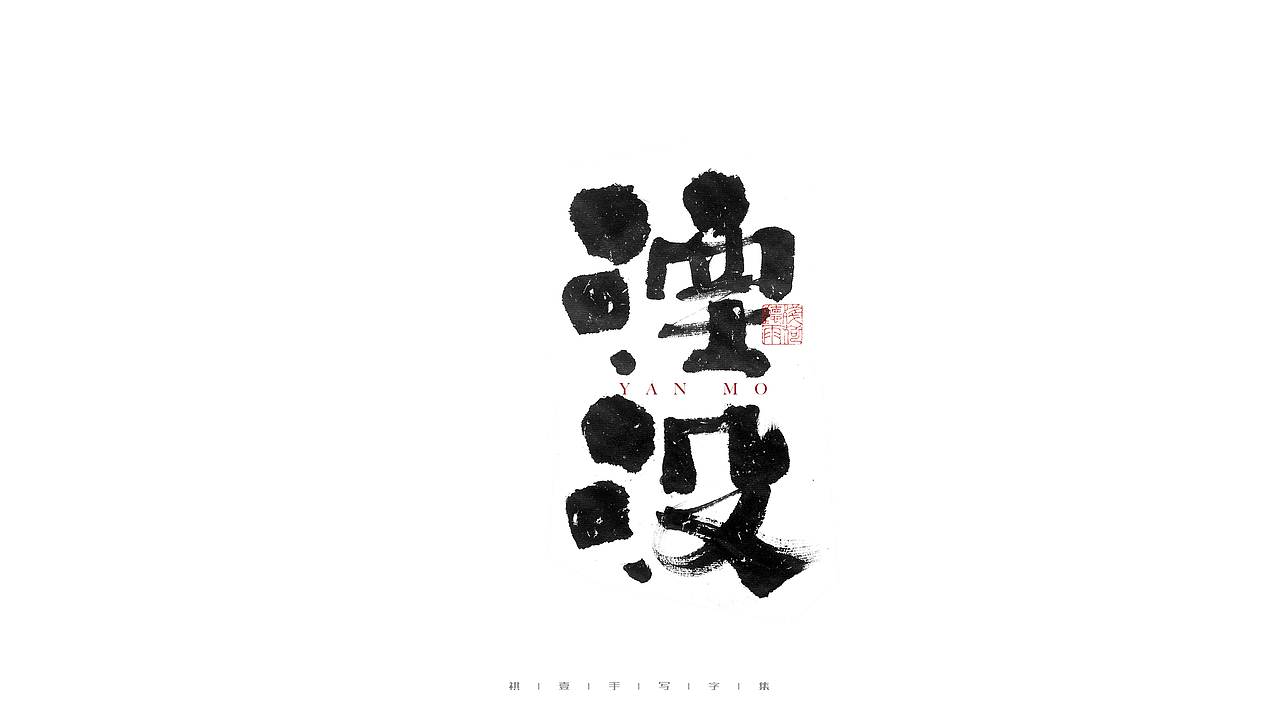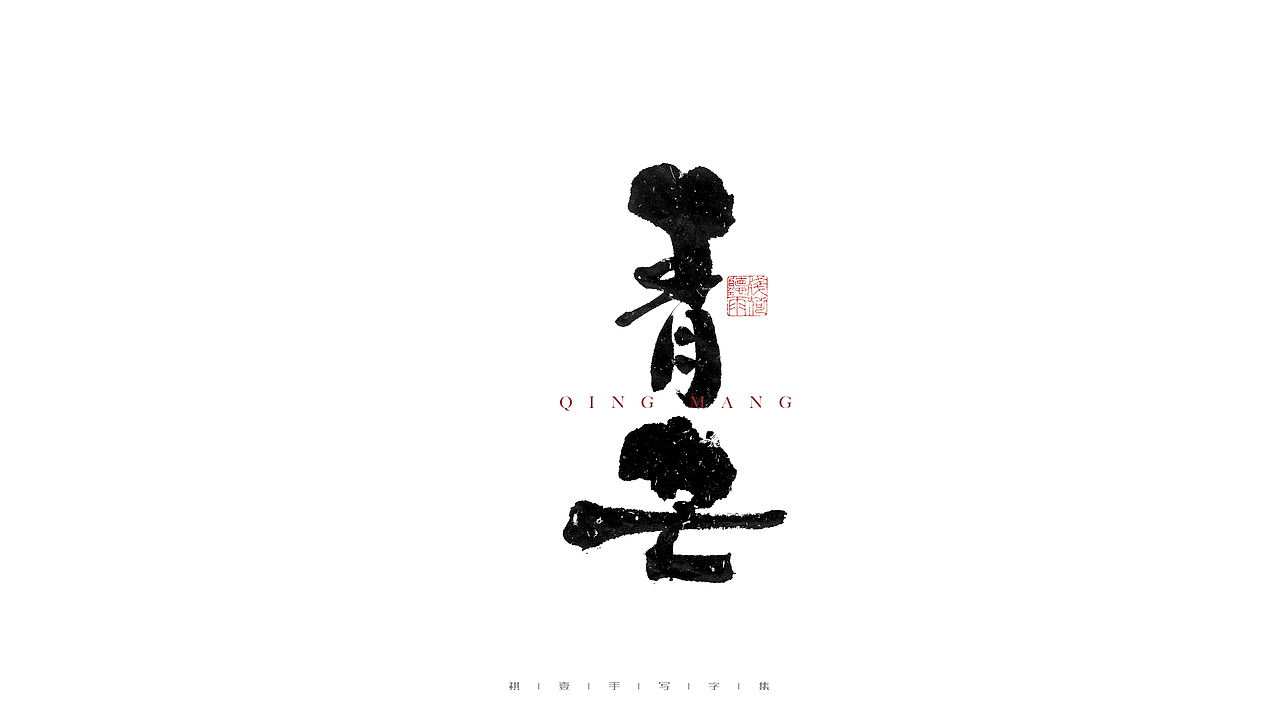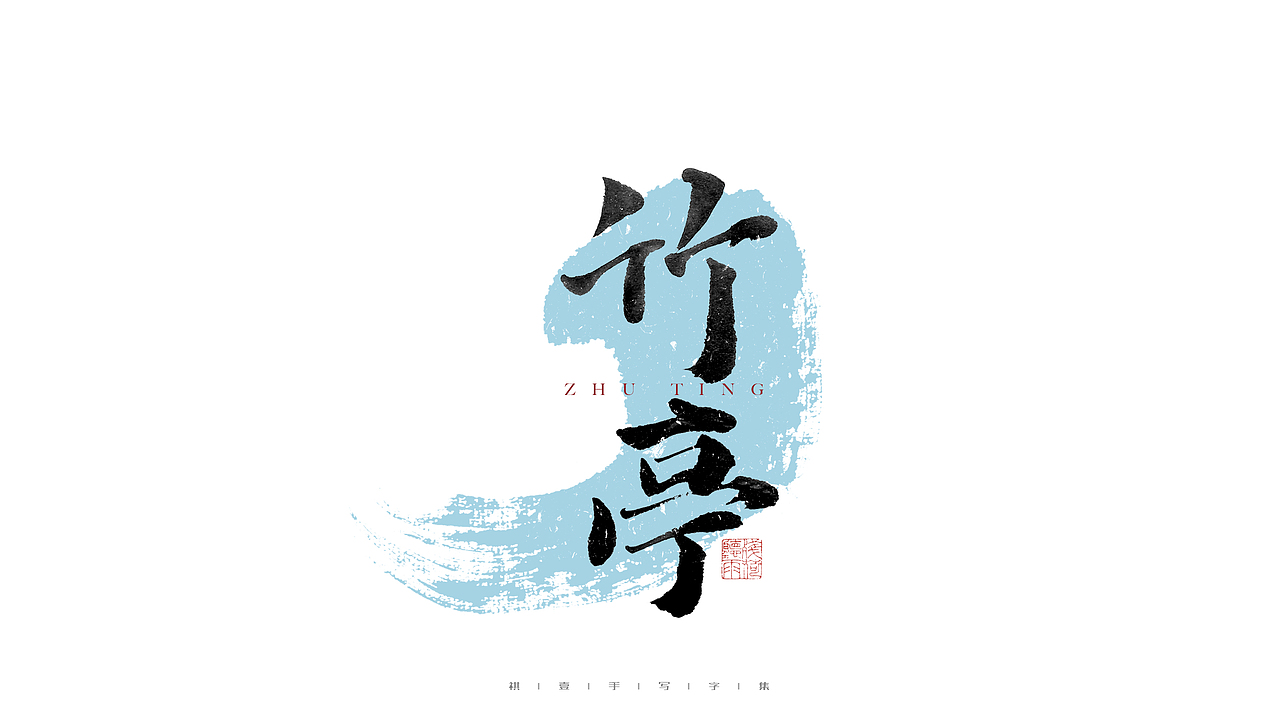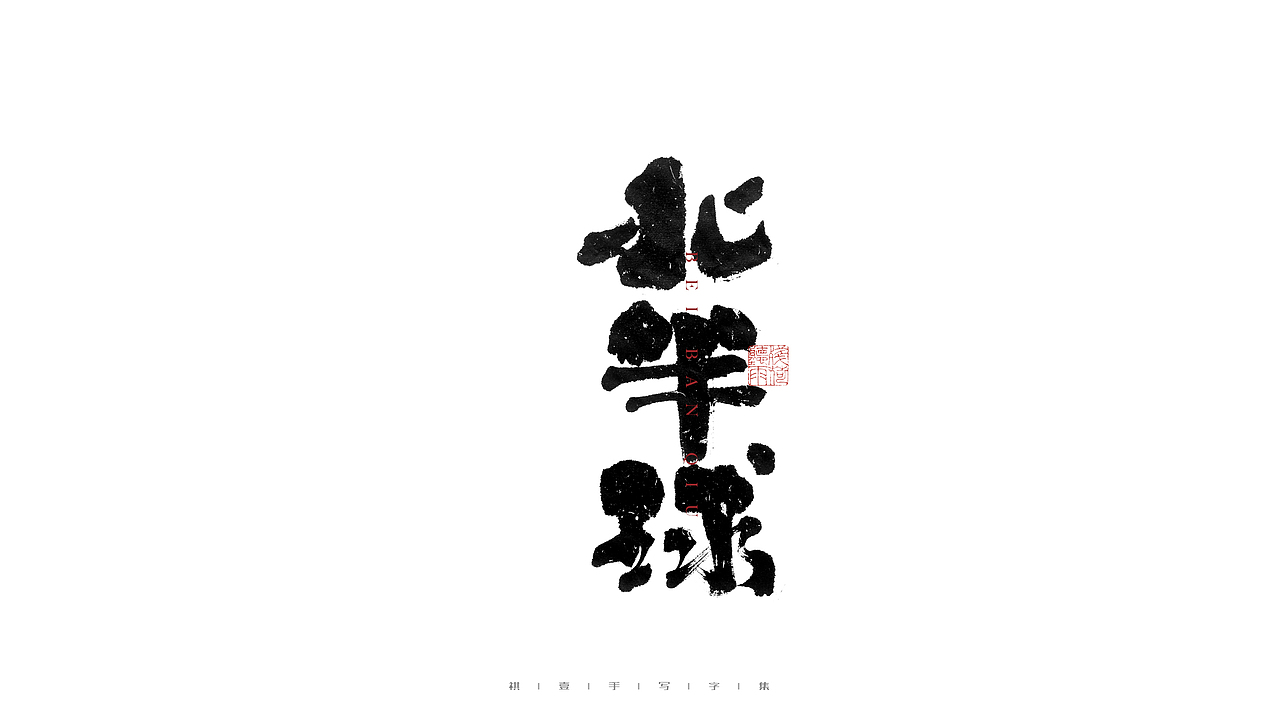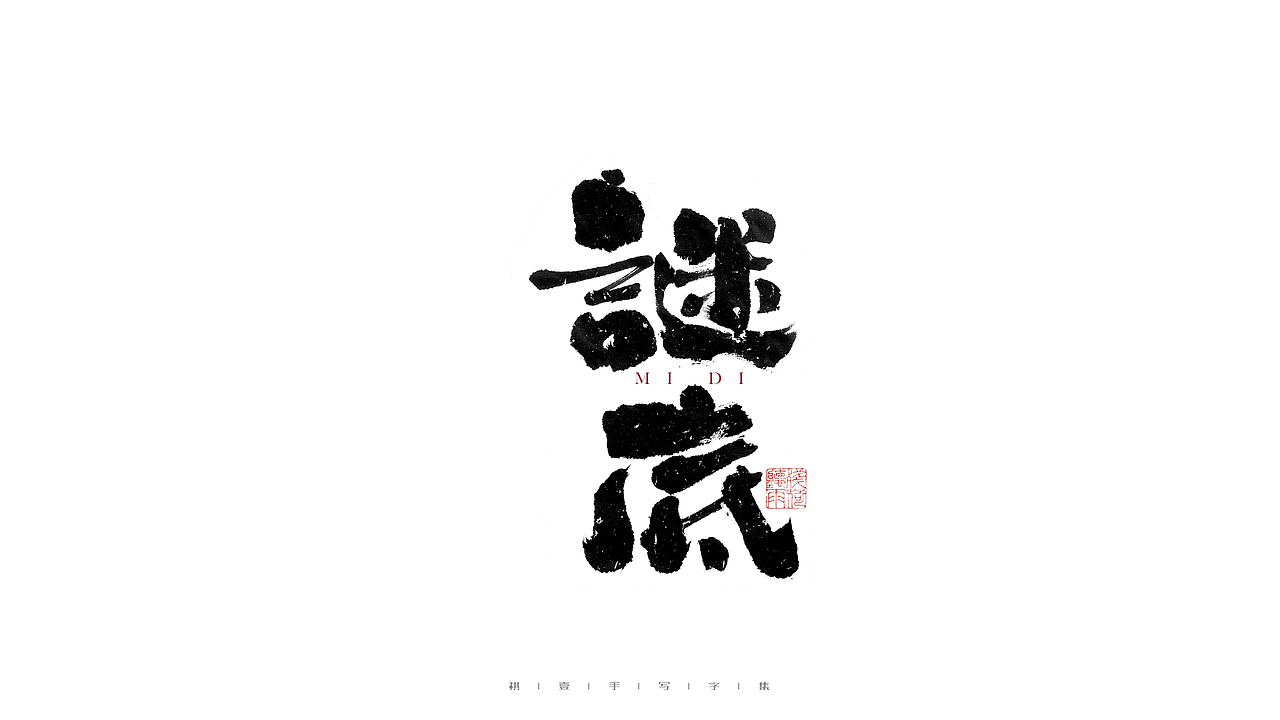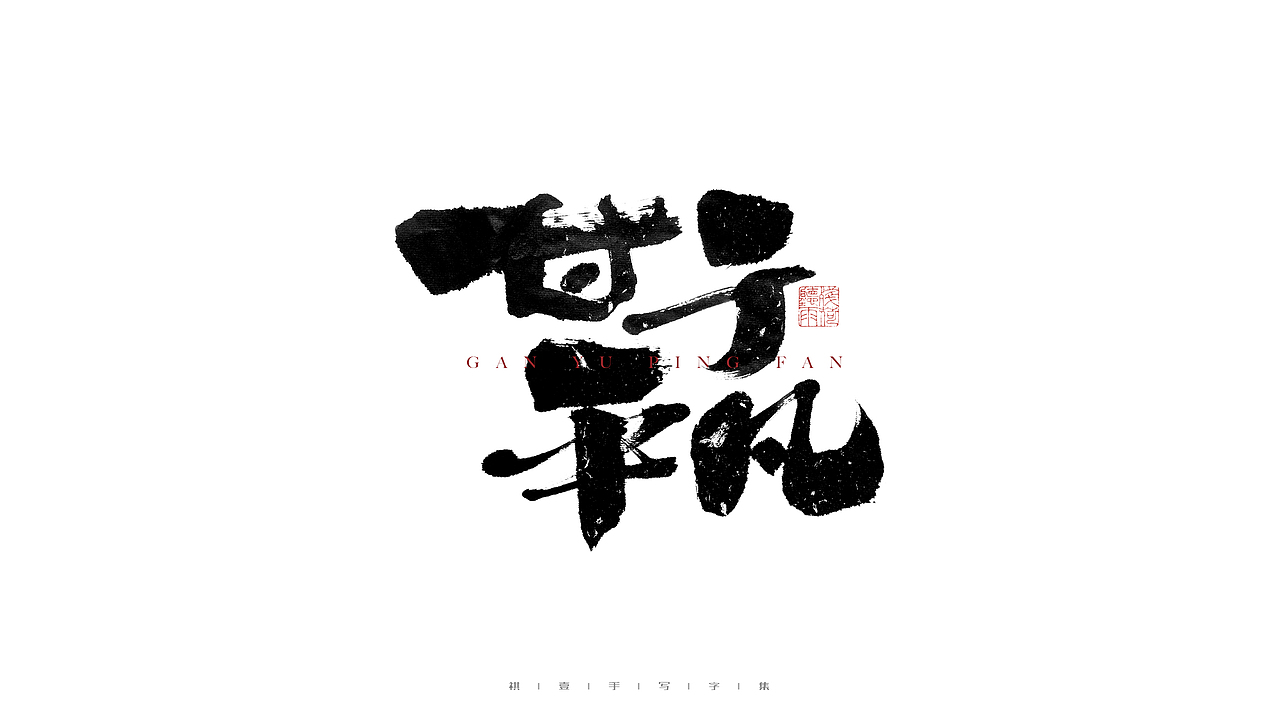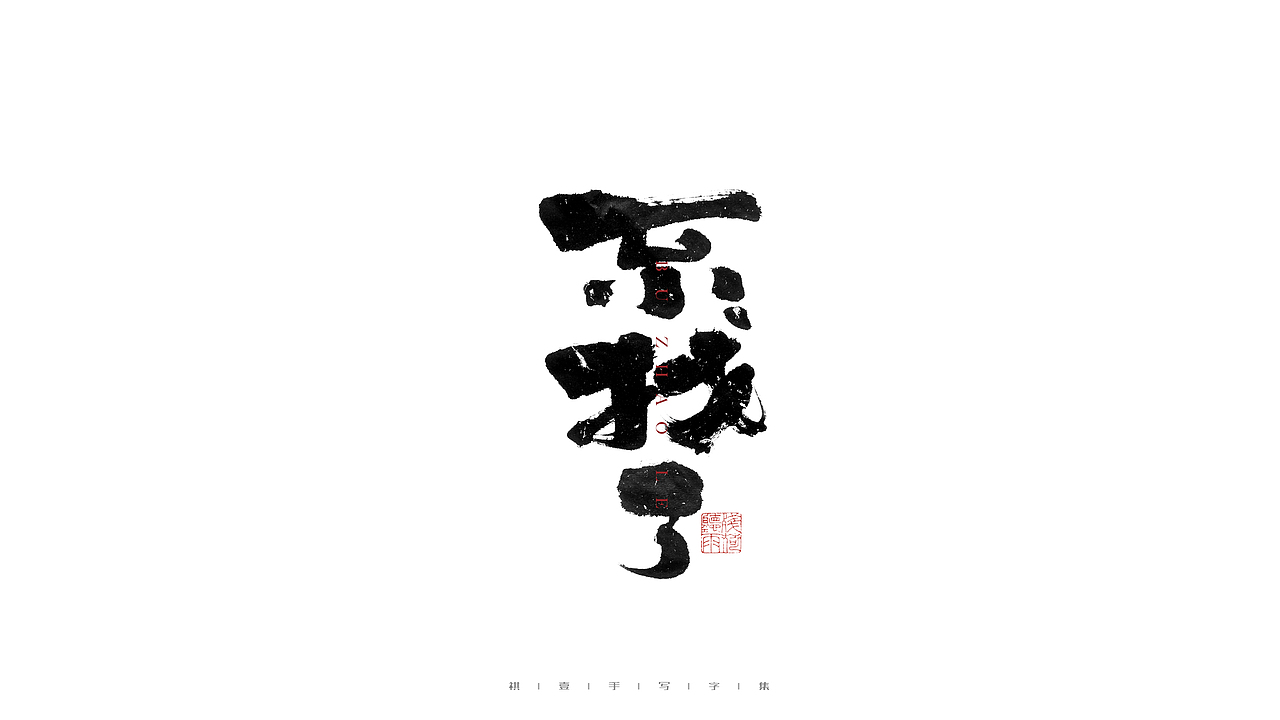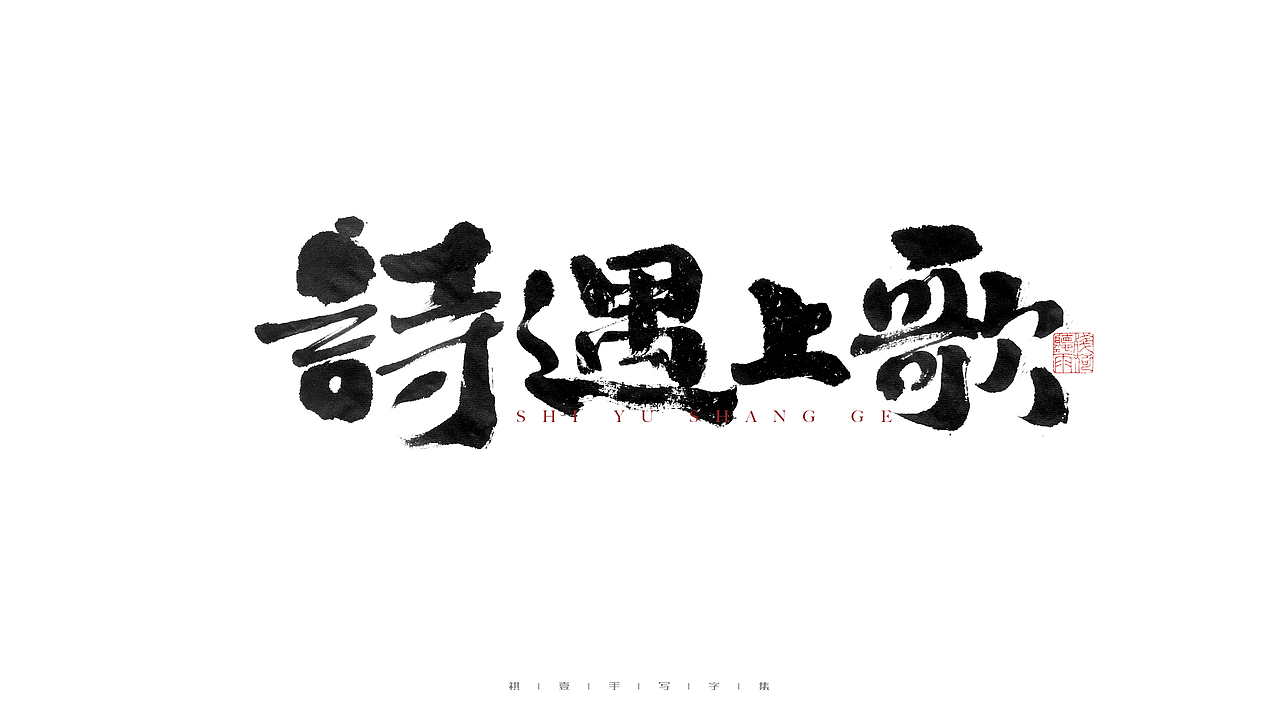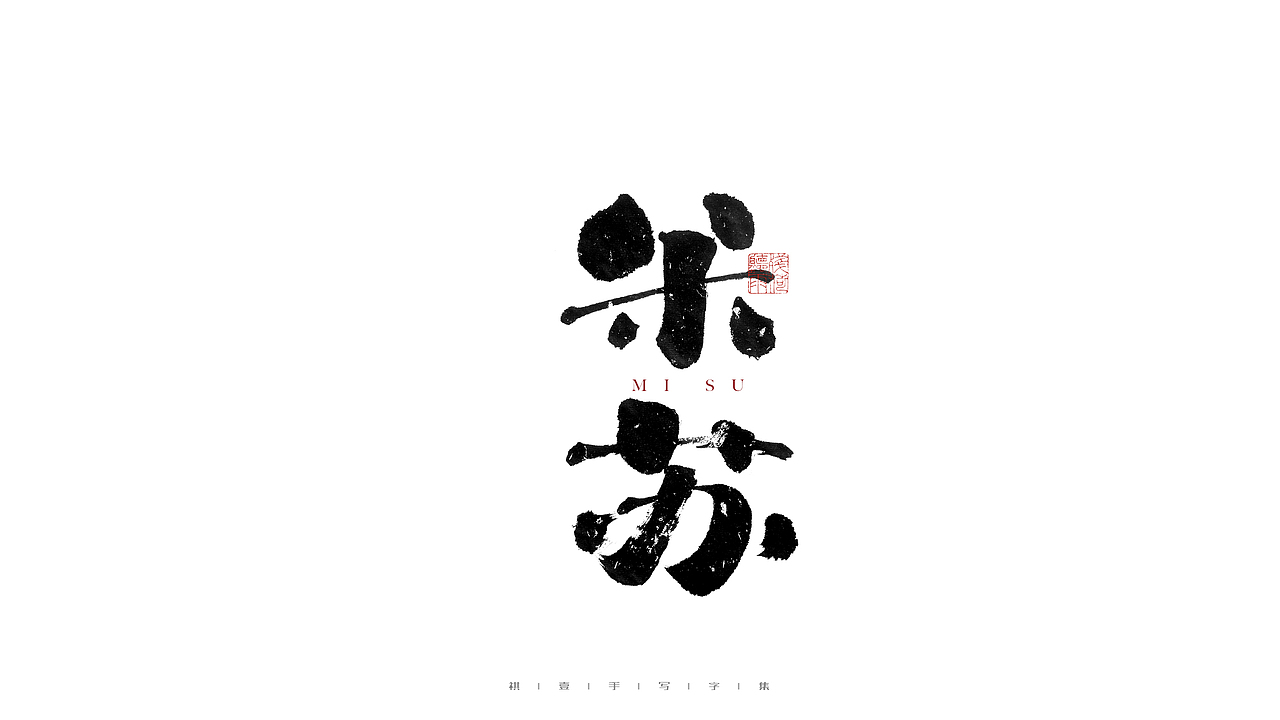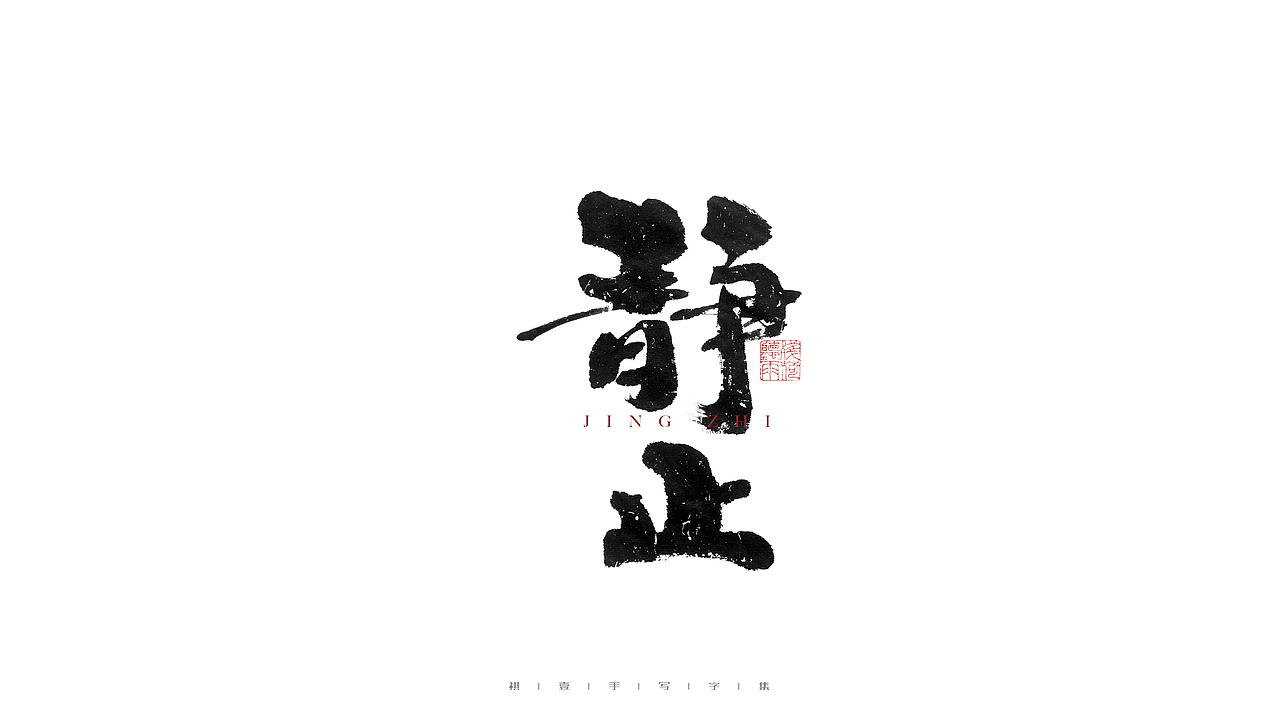
自言字语 —— 一组手写毛笔字(图ZMjc4NDg3NzQw) - 字体/字形 - 站酷设计师祺壹原创素材 - 站酷ZCOOL
自言字语 —— 一组手写毛笔字(图ZMjc4NDg3NjI4) - 字体/字形 - 站酷设计师祺壹原创素材 - 站酷ZCOOL
自言字语 —— 一组手写毛笔字(图ZMjc4NDg3Njky) - 字体/字形 - 站酷设计师祺壹原创素材 - 站酷ZCOOL
自言字语 —— 一组手写毛笔字(图ZMjc4NDg3NjMy) - 字体/字形 - 站酷设计师祺壹原创素材 - 站酷ZCOOL
自言字语 —— 一组手写毛笔字(图ZMjc4NDg3NjIw) - 字体/字形 - 站酷设计师祺壹原创素材 - 站酷ZCOOL
自言字语 —— 一组手写毛笔字(图ZMjc4NDg3NzI4) - 字体/字形 - 站酷设计师祺壹原创素材 - 站酷ZCOOL
自言字语 —— 一组手写毛笔字(图ZMjc4NDg3NjQ0) - 字体/字形 - 站酷设计师祺壹原创素材 - 站酷ZCOOL
自言字语 —— 一组手写毛笔字(图ZMjc4NDg3NjUy) - 字体/字形 - 站酷设计师祺壹原创素材 - 站酷ZCOOL
自言字语 —— 一组手写毛笔字(图ZMjc4NDg3NjY0) - 字体/字形 - 站酷设计师祺壹原创素材 - 站酷ZCOOL
自言字语 —— 一组手写毛笔字(图ZMjc4NDg3NzA0) - 字体/字形 - 站酷设计师祺壹原创素材 - 站酷ZCOOL
自言字语 —— 一组手写毛笔字(图ZMjc4NDg3NzAw) - 字体/字形 - 站酷设计师祺壹原创素材 - 站酷ZCOOL
自言字语 —— 一组手写毛笔字(图ZMjc4NDg3NjM2) - 字体/字形 - 站酷设计师祺壹原创素材 - 站酷ZCOOL
自言字语 —— 一组手写毛笔字(图ZMjc4NDg3NjEy) - 字体/字形 - 站酷设计师祺壹原创素材 - 站酷ZCOOL
自言字语 —— 一组手写毛笔字(图ZMjc4NDg3Njk2) - 字体/字形 - 站酷设计师祺壹原创素材 - 站酷ZCOOL
自言字语 —— 一组手写毛笔字(图ZMjc4NDg3NjI0) - 字体/字形 - 站酷设计师祺壹原创素材 - 站酷ZCOOL
自言字语 —— 一组手写毛笔字(图ZMjc4NDg3Njg0) - 字体/字形 - 站酷设计师祺壹原创素材 - 站酷ZCOOL
自言字语 —— 一组手写毛笔字(图ZMjc4NDg3NjE2) - 字体/字形 - 站酷设计师祺壹原创素材 - 站酷ZCOOL
自言字语 —— 一组手写毛笔字(图ZMjc4NDg3NjA4) - 字体/字形 - 站酷设计师祺壹原创素材 - 站酷ZCOOL
自言字语 —— 一组手写毛笔字(图ZMjc4NDg3NjA0) - 字体/字形 - 站酷设计师祺壹原创素材 - 站酷ZCOOL
自言字语 —— 一组手写毛笔字(图ZMjc4NDg3NjQ4) - 字体/字形 - 站酷设计师祺壹原创素材 - 站酷ZCOOL
自言字语 —— 一组手写毛笔字(图ZMjc4NDg3NjQw) - 字体/字形 - 站酷设计师祺壹原创素材 - 站酷ZCOOL
自言字语 —— 一组手写毛笔字(图ZMjc4NDg3Njg4) - 字体/字形 - 站酷设计师祺壹原创素材 - 站酷ZCOOL
自言字语 —— 一组手写毛笔字(图ZMjc4NDg3NjU2) - 字体/字形 - 站酷设计师祺壹原创素材 - 站酷ZCOOL
自言字语 —— 一组手写毛笔字(图ZMjc4NDg3NjYw) - 字体/字形 - 站酷设计师祺壹原创素材 - 站酷ZCOOL
自言字语 —— 一组手写毛笔字(图ZMjc4NDg3NjY4) - 字体/字形 - 站酷设计师祺壹原创素材 - 站酷ZCOOL
自言字语 —— 一组手写毛笔字(图ZMjc4NDg3Njcy) - 字体/字形 - 站酷设计师祺壹原创素材 - 站酷ZCOOL
自言字语 —— 一组手写毛笔字(图ZMjc4NDg3Njc2) - 字体/字形 - 站酷设计师祺壹原创素材 - 站酷ZCOOL
自言字语 —— 一组手写毛笔字(图ZMjc4NDg3Njgw) - 字体/字形 - 站酷设计师祺壹原创素材 - 站酷ZCOOL
自言字语 —— 一组手写毛笔字(图ZMjc4NDg3NzA4) - 字体/字形 - 站酷设计师祺壹原创素材 - 站酷ZCOOL
自言字语 —— 一组手写毛笔字(图ZMjc4NDg3NzEy) - 字体/字形 - 站酷设计师祺壹原创素材 - 站酷ZCOOL
自言字语 —— 一组手写毛笔字(图ZMjc4NDg3NzQ0) - 字体/字形 - 站酷设计师祺壹原创素材 - 站酷ZCOOL
自言字语 —— 一组手写毛笔字(图ZMjc4NDg3NzMy) - 字体/字形 - 站酷设计师祺壹原创素材 - 站酷ZCOOL
自言字语 —— 一组手写毛笔字(图ZMjc4NDg3NzE2) - 字体/字形 - 站酷设计师祺壹原创素材 - 站酷ZCOOL
自言字语 —— 一组手写毛笔字(图ZMjc4NDg3NzIw) - 字体/字形 - 站酷设计师祺壹原创素材 - 站酷ZCOOL
自言字语 —— 一组手写毛笔字(图ZMjc4NDg3NzI0) - 字体/字形 - 站酷设计师祺壹原创素材 - 站酷ZCOOL
自言字语 —— 一组手写毛笔字(图ZMjc4NDg3NzM2) - 字体/字形 - 站酷设计师祺壹原创素材 - 站酷ZCOOL